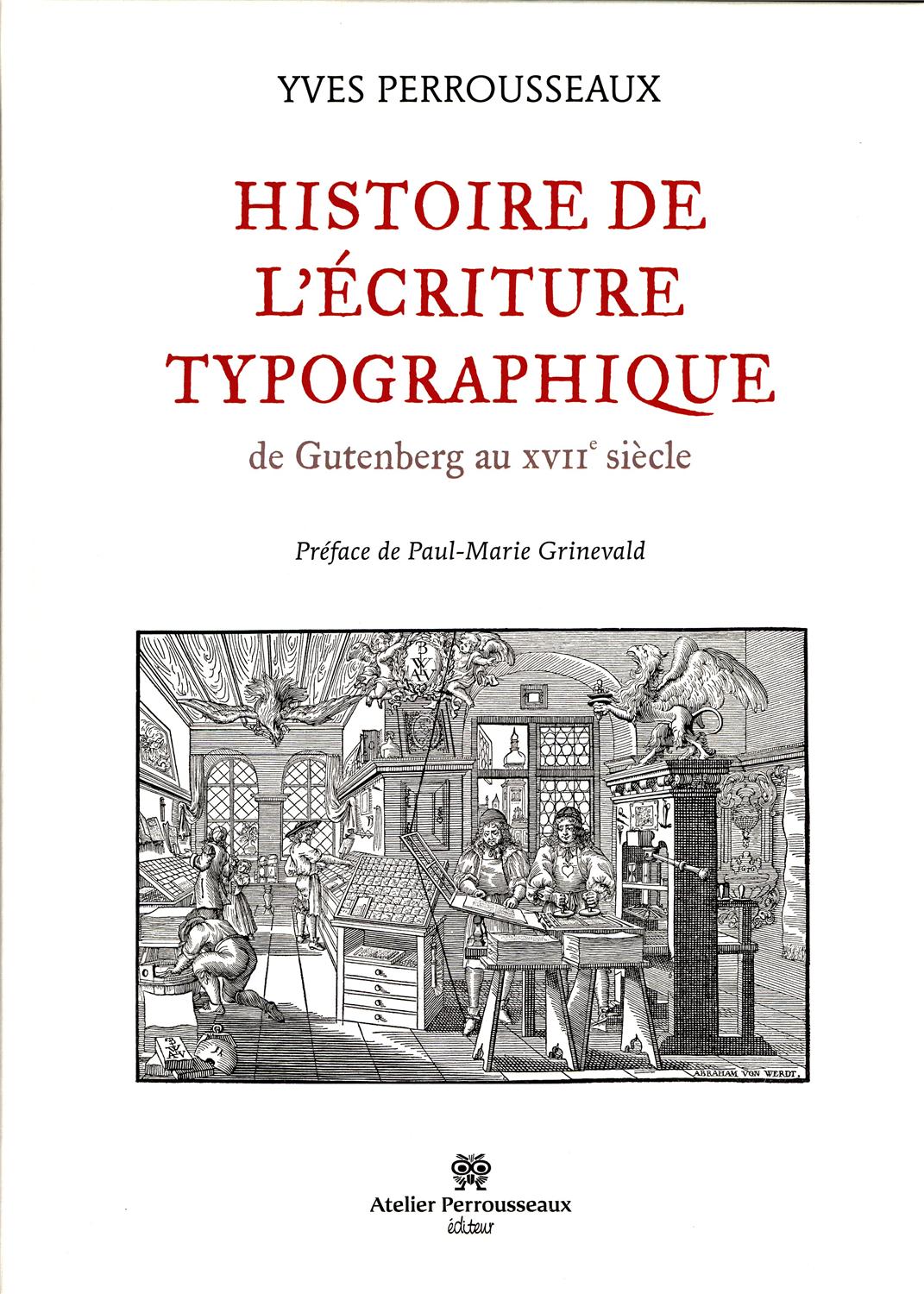
HISTOIRE DE L'ÉCRITURE TYPOGRAPHIQUE - DE GUTENBERG AU XVIIEME SIÈCLE
Livre neuf. Histoire de l'écriture typographique de Gutenberg au XVIIe siècle. Ce livre raconte, avec prés de 700 illustrations, plusieurs siècles d'histoire dans laquelle des créateurs de caractères et des imprimeurs ont marqué la naissance et l'évolution de la typographie...